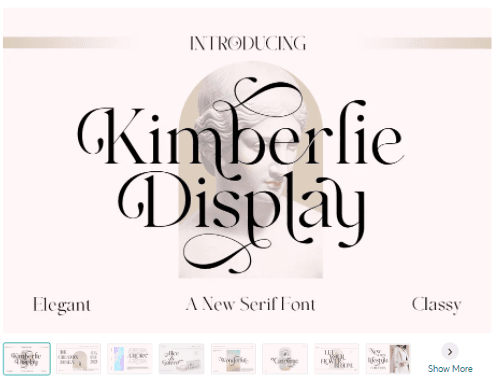
Kimberlie Display Font
Kimberlie - это роскошный дисплей с засечками с уникальным характером, сочетающий геометрические формы с органическими изогнутыми деталями. Это уникальный шрифт для вашей индивидуальности. Вдохновленный старым шрифтом с засечками и современным шрифтом с засечками. Чрезвычайный контраст между толстыми и тонкими мазками дает гармоничный и стильный вид. Элегантный и чувственный дидон с засечками, усиленный лигатурами, чередованиями и росчерками. Kimberlie предлагает OpenType с 1025+ символами, 210 стилистическими альтернативами, 486 лигатурами. Идеально подходит для широкого спектра применений. От поздравительных открыток до журналов, свадебных приглашений, логотипов на веб-сайты и т. Д.